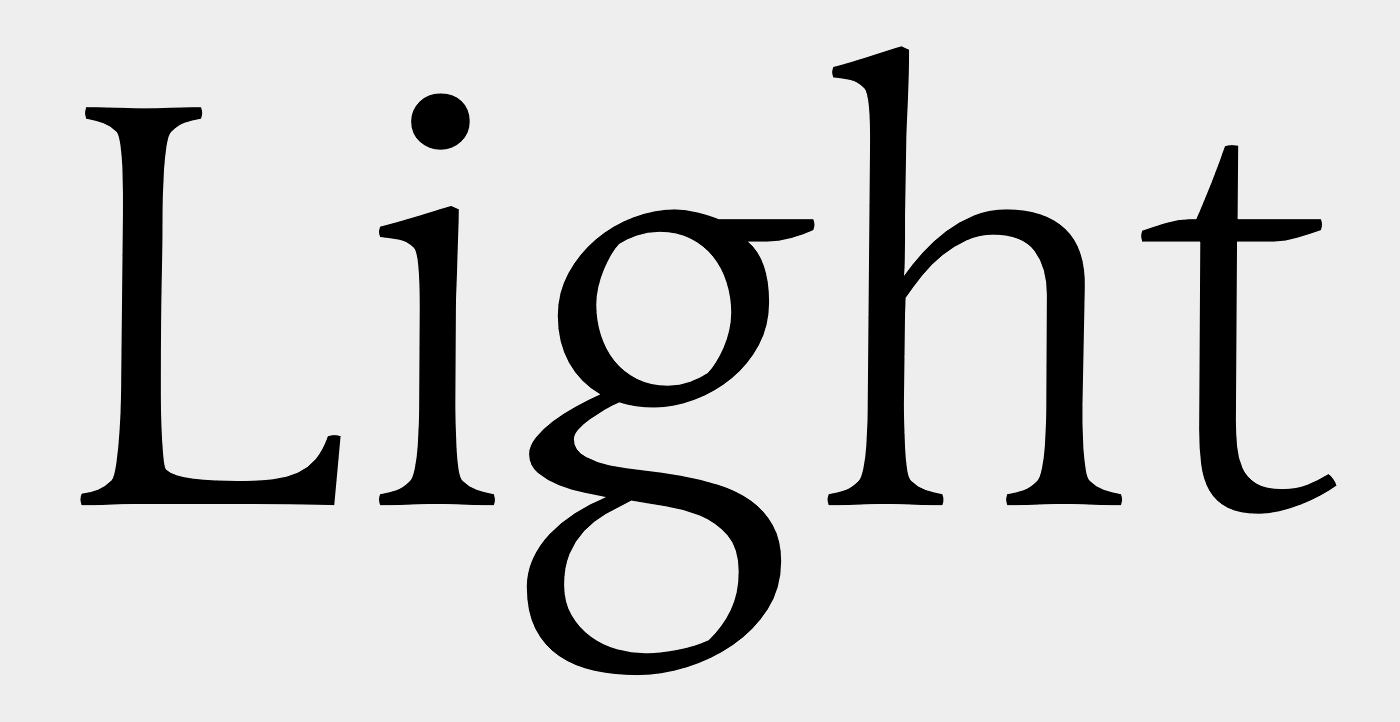
Passende Serifenschrift zu Linotype-Aroma
ich bin auf der Suche nach einer Serifenschrift für den Fließtext eines Buches, die zur Linotype-Aroma-Light (die im Buch als Schrift für bestimmte Textarten verwendet wird) passt.
Bisher getestet habe ich die Adobe und Stempel Garamond. Allerdings finde ich, dass sie nicht ganz mit dem Charakter der Aroma harmonisieren. Ich denke es müsste eine etwas dynamischere, ausgefallenere Serifenschrift als die üblichen Verdächtigen sein. Sollte aber dennoch gut lesbar sein.
Was meint ihr, was für eine Serifenschrift passt zur Aroma?
Aroma:
Adobe Garamond:
Adobe Stempel:
Die kam mir aufgrund des g auch sofort in den Sinn. Die Aroma wirkt aber auch leicht holzschnittartig. Daher könnten evtl. auch scharfkantigere Schriften wie FF Yoga, FF Dora, FF Tundra passen. Und schön dynamisch ist auch die FF Quadraat.